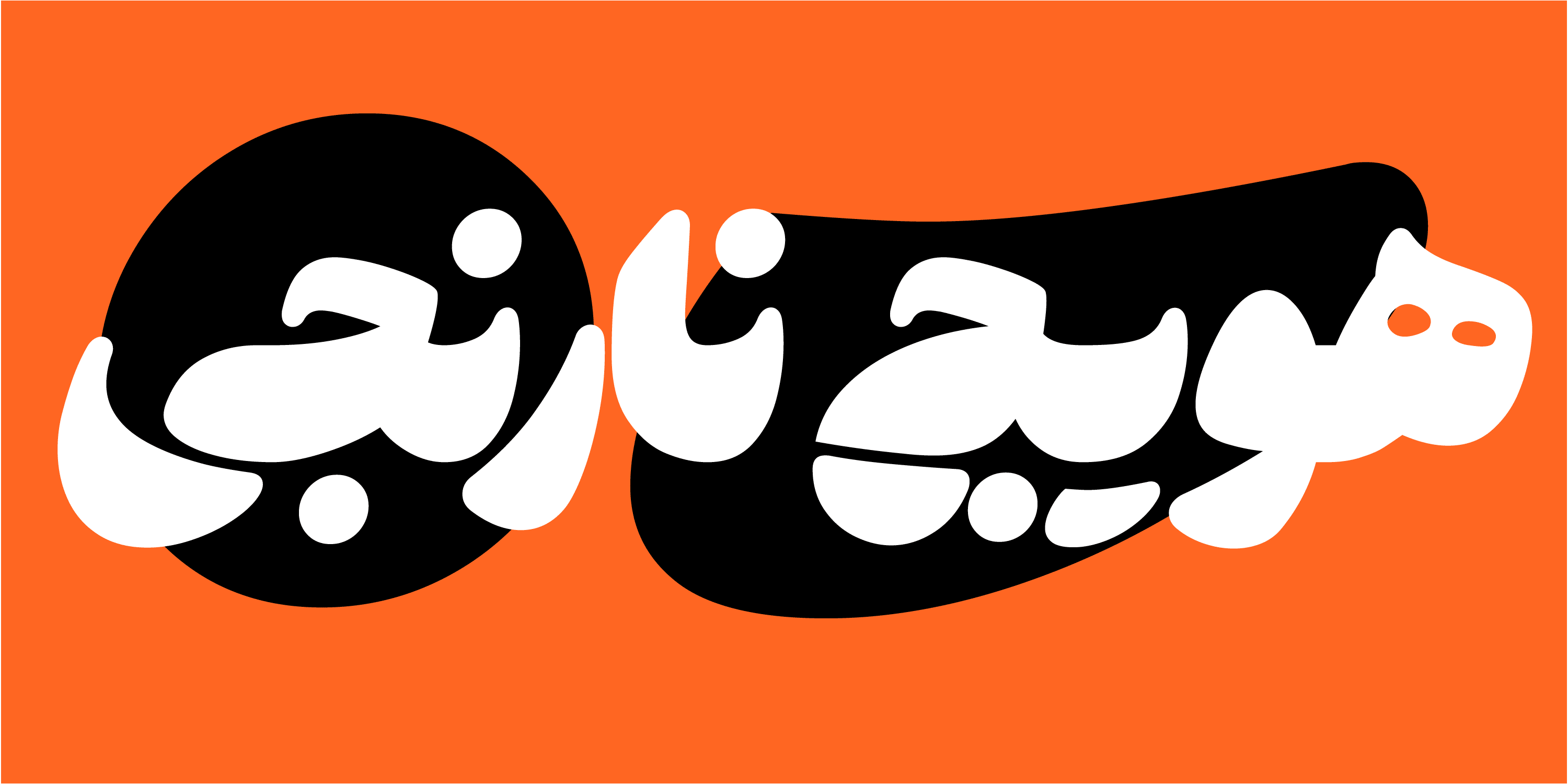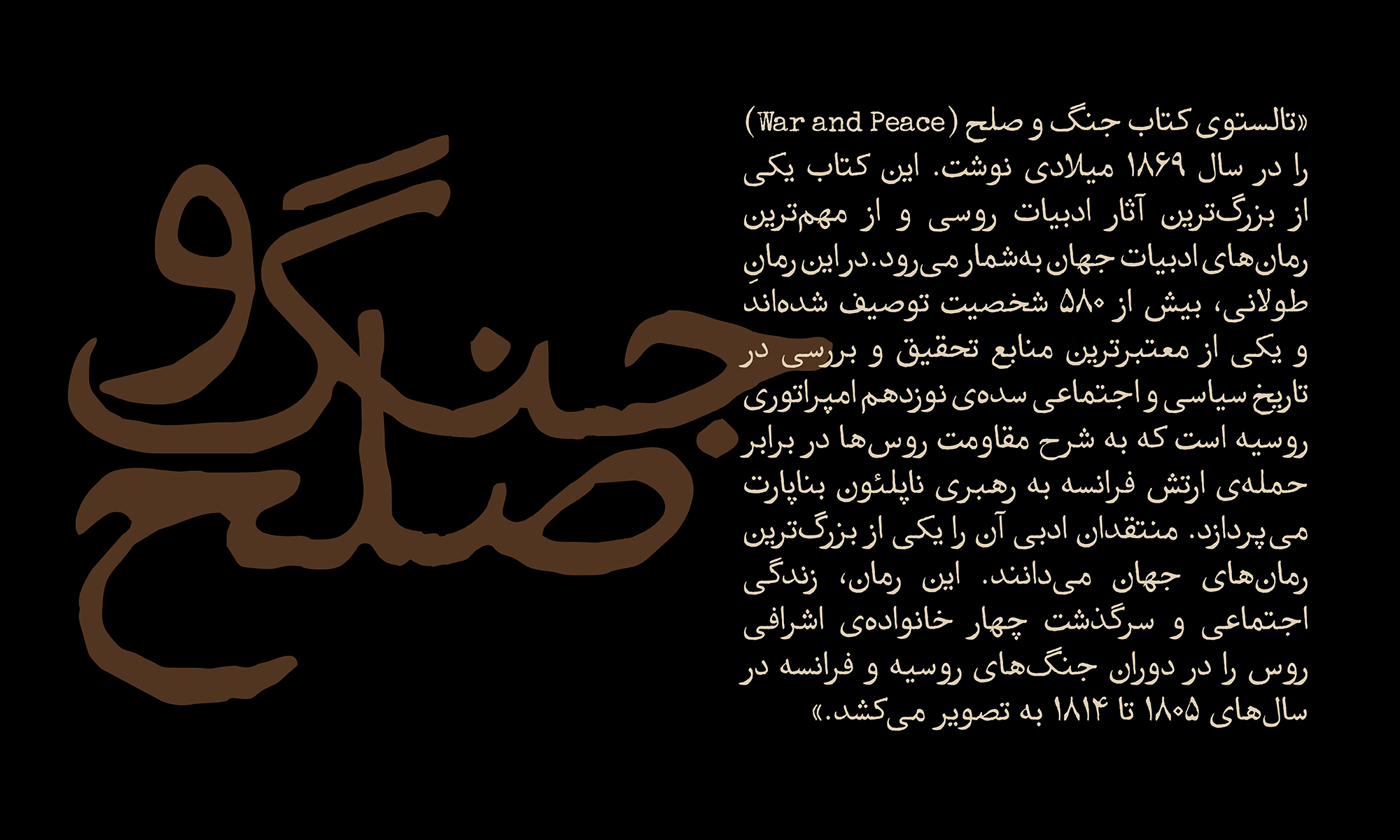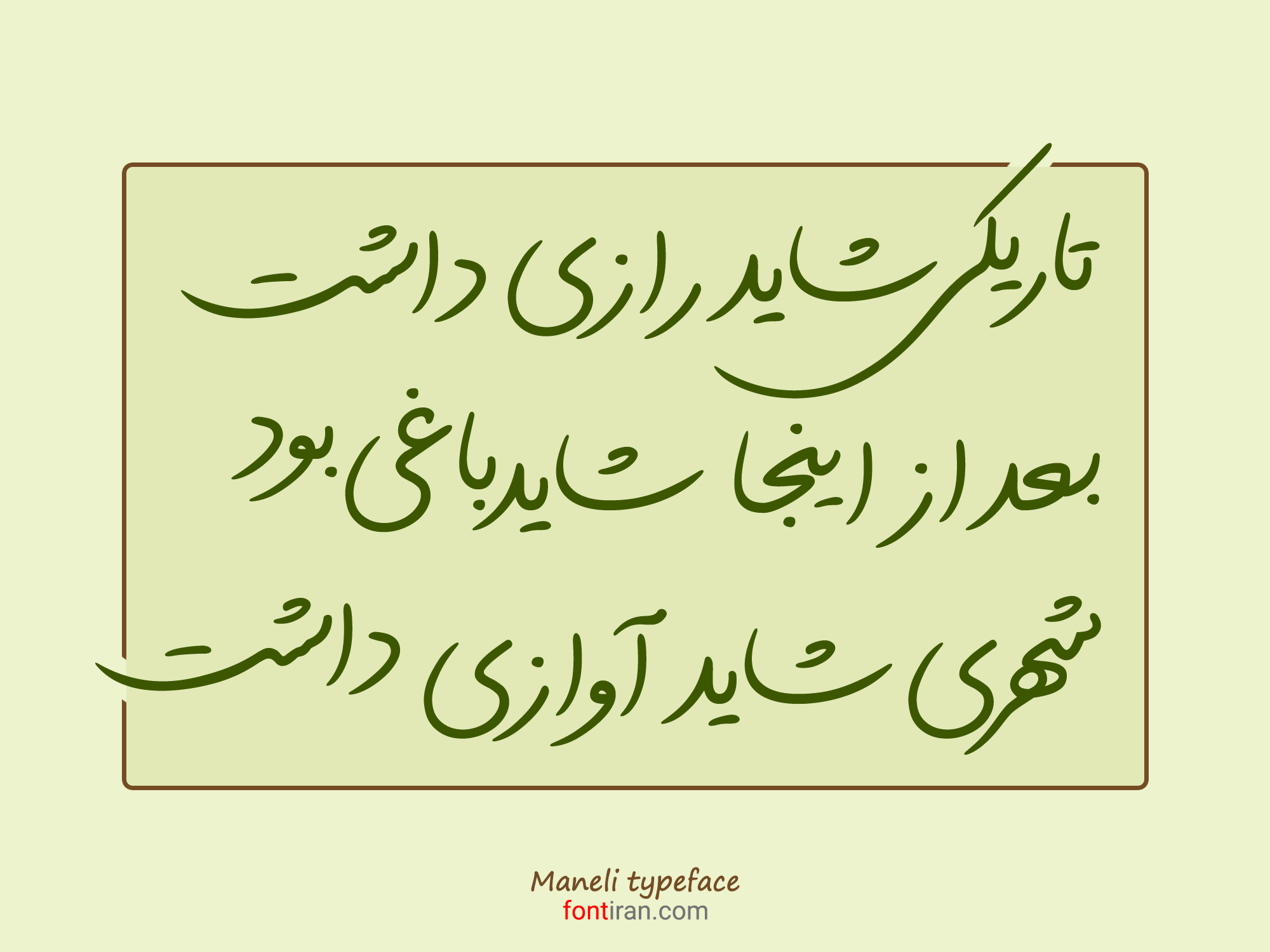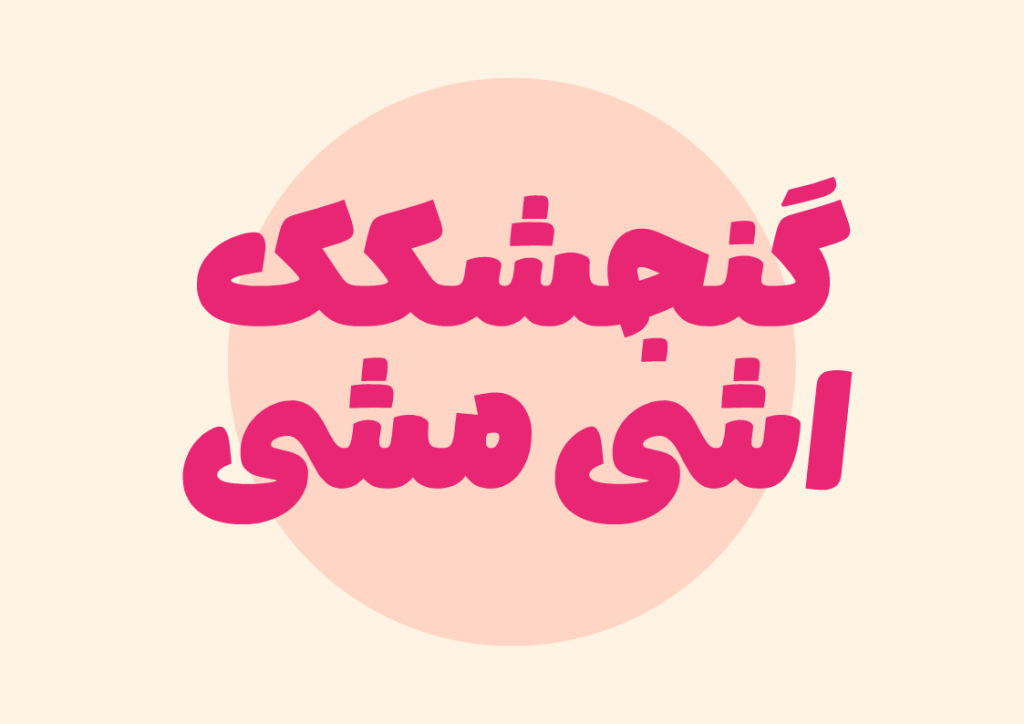
سلام احتمالا الان شما به دنبال دانلود فونت زیبا واسه طراحی ها و تولید و محتواهاتون هستید. فونتی که باید خفن باشه بهترین باشه جدید باشه به روز باشه و خیلی ویژگی های زیاد دیگه. با ما همراه باشید تا توی این مقاله به معرفی انواع فونت ها و دسته بندی های مختلف از تایپ فیس های فارسی بپردازیم و اون ها رو به شما دوستان عزیز معرفی کنیم.
قبل از ارائه توضیحات در رابطه با دسته بندی، کاربرد، ویژگی ها و امکانات فونت های مختلف در تصاویر زیر نمونه ای از بهترین و زیباترین تایپ فیس ها و فونت ها رو به همراه توضیح کوتاه برای شما در اسلایدر زیر آوردیم. که هرکدوم رو دوست داشتین می تونین مشاهده و دانلود کنید.
هدف ما توی این مقاله معرفی فونت زیبا برای دانلود به شماست. و در ادامه قصد داریم شاخص های یک فونت خوب رو به شما معرفی کنیم.
اما ابتدا نیاز داریم تا یک توضیح اجمالی و کوتاه از روند پیشرفت خط تا تولد تایپوگرافی و فونت رو واسه شما توضیح بدیم. ما برای اینکه بتونیم مفهوم رعایت قائده و قواعد در خوشنویسی رو توضیح بدیم لازمه این نکته رو بگیم که خط اولیه از شکل ها و علائم تشکیل شد. سپس حروف الفبا اومدن و خط به سمت دست نویسی رفت در ادامه با قاعده مند شدن و رعایت یک سری قانون ها به خوشنویسی رسید با ظهور صنعت چاپ و ماشین ها به مرور تایپ ، تایپوگرافی و فونت وارد ادبیات امروزی بشر شد.
این یک توضیح اجمالی از تاریخچه پیدایش خط تا ظهور تایپوگرافی و فونت بود. نیاز بود تا این مقدمه رو بدونید تا در ادامه بهتر بتونیم مطالب رو واسه شما عزیزان ارائه بدیم.
شما عزیزان به دنبال مشخصه های یک فونت زیبا و خوب و مناسب هستید واسه نوشته ها مقالات جلد کتاب ها پست های وب سایت یا شبکه های اجتماعی و هزاران کاربرد دیگه به اون ها نیاز دارید فونت ها با تلاش و همت طراحان به روز میشن و نیاز ما برای تولید نوشته ها و محتوا های جدید به اون ها ضروریه.
خوانایی یا نمایشی بودن مسئله این است!
یکی از مهم ترین ویژگی های یک فونت زیبا برای دانلود دارا بودن ویژگی خوانایی اون هست . چرا که اساسا هدف ابتدایی از ساخت تایپ فیس و فونت خواندن هست. اگه نوشته ها و متن روان و صحیح خونده نشه اصلا فونت به چه دردی میخوره ؟! این ویژگی بیشتر خودش رو در متون ریز و بلند نمایش می ده به عبارت دیگر ویژگی خوانایی یک فونت در متون ریز و بلند بسیار حیاتی و ضروریه. خوانایی برای تایپ فیس های متن ساخته شده. برای انواع متن ها از کتاب و مجله و مقاله گرفته تا وب سایت ها و شبکه های اجتماعی و …
دانلود فونت های زیبا برای متن با خوانایی بالا
خب همون طور که گفته شد اصولا فونت هایی که برای متن ساخته و طراحی میشن اصولا باید دارای ویژگی خوانایی بالایی باشن تا مخاطبین خودشون رو در طی خوندن یک متن ریز و بلند که روان و سلیس خونده بشه همراهی کنند. می تونید از طریق لینک زیروارد قسمت فونت های متن بشید که نمونه ای از زیباترین فونت ها واسه دانلود در اون قرار داده شده.
دسته بندی تایپ فیس هایی با ویژگی خوانایی بالا
اما ویژگی دیگری که برای یک تایپ فیس و فونت، زیبایی رو به ارمغان میاره. جاذبه های بصری و دیداری اون یا همان بهره مند بودن از ویژگی نمایشی هست. فونت باید علاوه بر خوانایی بالا دارای آنچنان ظرافت های طراحی باشه تا چشم ها را به خودش بدوزه و نگاه ها رو خیره کنه. در اینصورت هست که یک تایپ فیس می درخشه.
ویژگی نمایشی با بهره بردن از ابزار های مختلف ازجمله کنتراست سطحی، ظرافت های طراحی تشکیل میشه. و در اوزان سنگین خود را بیشتر به نمایش میذاره. معمولا از این ویژگی جهت عناوین و تیتر های تبلیغاتی مطبوعاتی و … در تمامی زمینه ها از صنعت چاپ و نشر گرفته تا فضای وب و دیجیتال استفاده میشه. با فونت زیبا تا انتهای این مقاله همراه ما باشید.
نمایشی ویژگی مهم فونت های عناوین
فونت های عنوان برای تیتر ها و عناوین و متون کوتاه هستند ویژگی نمایشی و جذب مخاطب از اهمیت فوق العاده ای در این دسته برخورداره .
دسته بندی تایپ فیس هایی با ویژگی نمایشی بالا
دسته بندی فونت ها بر اساس رعایت قوائد
تایپ فیس ها و فونت های فارسی از جنبه های دیگه ای هم میتونن دسته بندی بشن. یکی از این نوع دسته بندی ها رعایت فرم های طراحی حروف و گلیف ها بر اساس یک قائده و قانونه . قبلا گفتیم که پس از ابداع الفبا انسان ها شروع به دست نویسی کردن نیاز به ایجاد قائده و قانونی برای این دست نویسی احساس شد که نتیجه اون خوشنویسی بود . خطوط خوشنویسی متولد شد از جمله خط نسخ، ثلث، کوفی و …
فونت های فارسی از این حیث به دسته بندی های مختلف تقسیم میشن. خط خوشنویسی نسخ یکی از خطوط قدیمی و ماندگار هست که بسیاری از فونت ها و قلم های فارسی با پیروی از قواعد و قوانین موجود در اون تشکیل و الهام گرفته .
به همین ترتیب خط سنس رو هم داریم برخی دیگه از تایپ فیس ها هم اقتباس گرفته از قوائد موجود در این نوع از خط می باشند. البته توی این مقاله قصد توضیح قواعد و قوانین خوشنویسی خط نسخ یا سنس رو نداریم ولی اگر مایل به داشتن اطلاعات از خطوط خوشنویسی هستید میتونید مقاله تفاوت خوشنویسی و دست نویسی رو مطالعه کنید. توی این مقاله اشاره به روند شکل گیری اصول و و قائده مند کردن برای خلق خوشنویسی شده است.
خب تا این جای کار دو نوع از دسته بندی های رو برای شما ذکر کردیم خط نسخ و خط سنس تا کنون بسیاری از بهترین و زیباترین فونت های و قلم های فارسی از این دو خط ساخته و الهام گرفته اند. اما دسته ای دیگر هم از تایپ فیس ها و فونت های فارسی وجود دارند که هیچ کدام از قائده های خطوط خوشنویسی نسخ و سنس در اونها دیده نمیشه. اما دارای جاذبه ها و زیبایی های بی شماری هم هستند و کاربردهای خاص خودشون رو هم دارند.
این دسته از فونت های زیبا با عنوان هندسی شناخته میشن و عمدتا از اشکال هندسی، زوایا و منحنی ها تشکیل شده اند. رابط های کاربری خاص خودشون رو دارند . و عمدتا مناسب محیط های امروزی و مدرن و فضاهای جدید از جمله وب سایت ها و شبکه های اجتماعی برای تبلیغات بیلبوردها پست ها و بسیاری از کاربرد ها هستند.